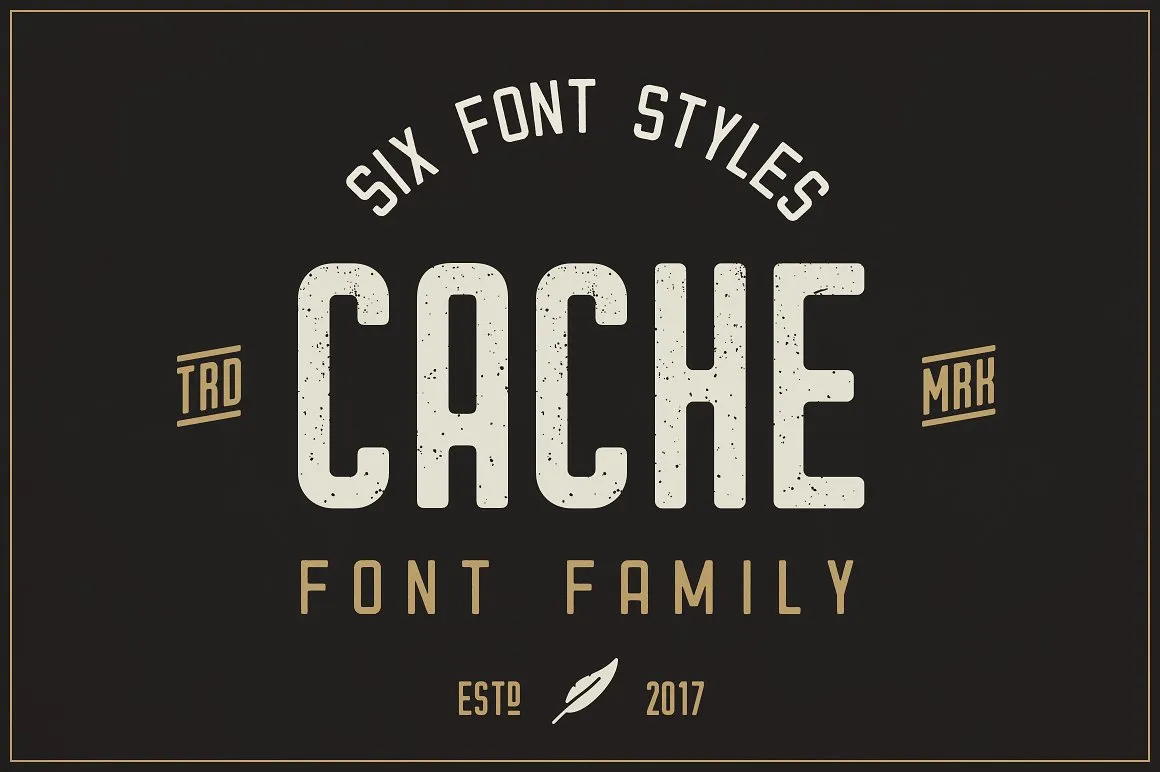
Descubra uma nova fonte para seus projetos visuais com Cache Font Family. Especialmente criada por Quill Type Co, essa fonte premium é agora gratuita para download e está disponível na CreativeMarket. Com a Cache você encontrará um amplo leque de estilos: Regular, Rough e Pressed, cada um acompanhado de uma variante estilizada (obliúgica). O estilo Rough não apenas oferece um visual vintage clássico, mas também apresenta texturas elaboradas por mão dura para garantir que cada característica tenha seu próprio padrão único. Esta característica adicional torna a Cache Font Family perfeita para uso em logotipos, posters, roupas e sinais de localização. Com sua aparência autêntica vintage, você conseguirá exatamente o resultado desejado em seus projetos visuais.